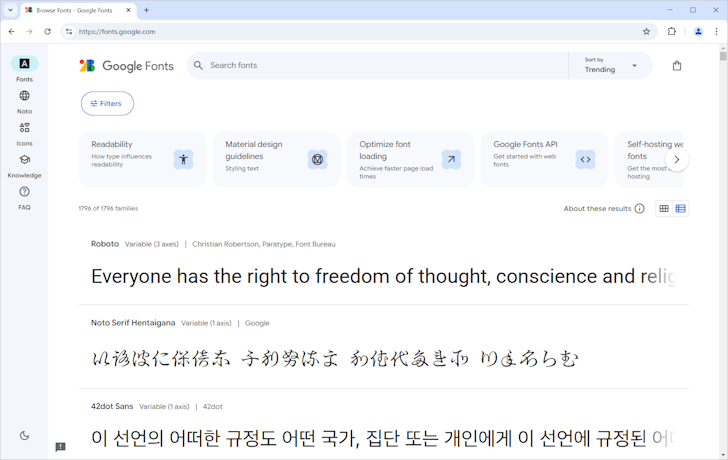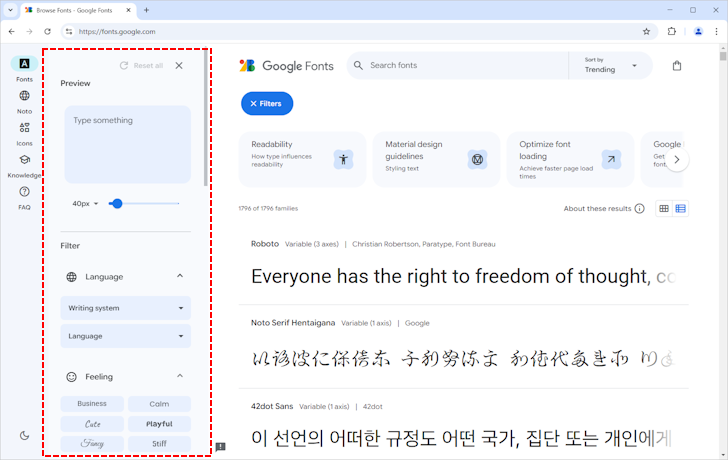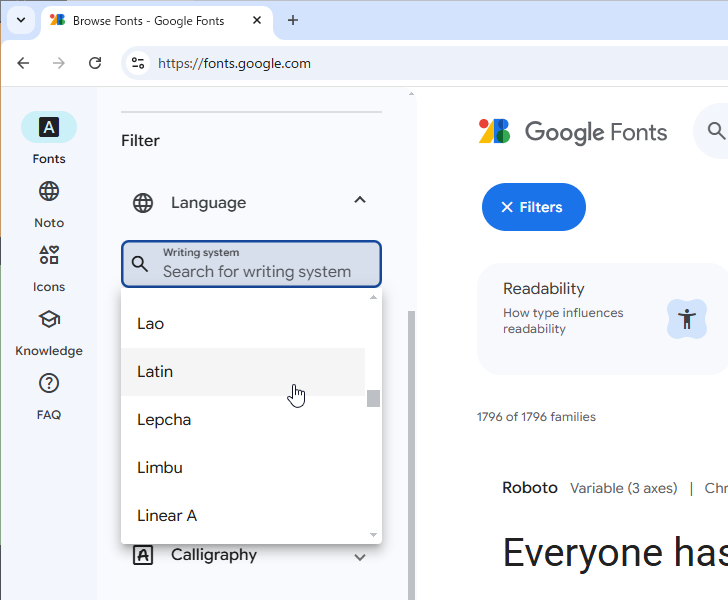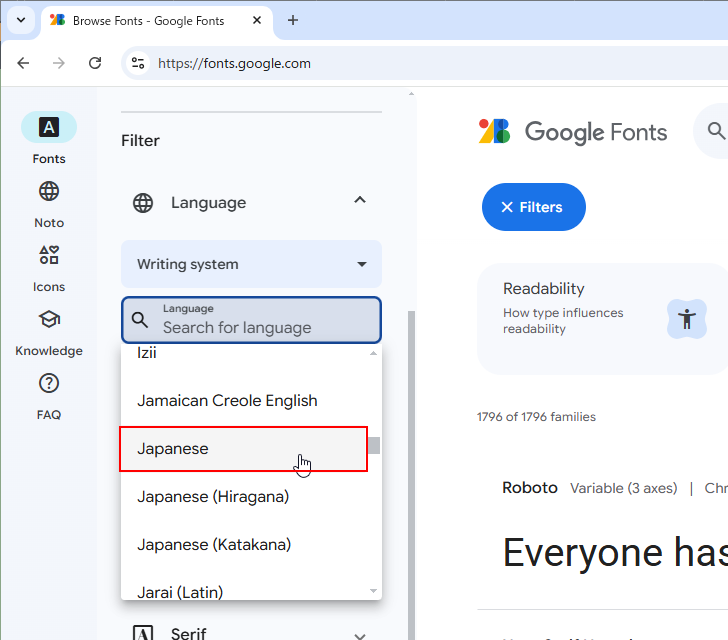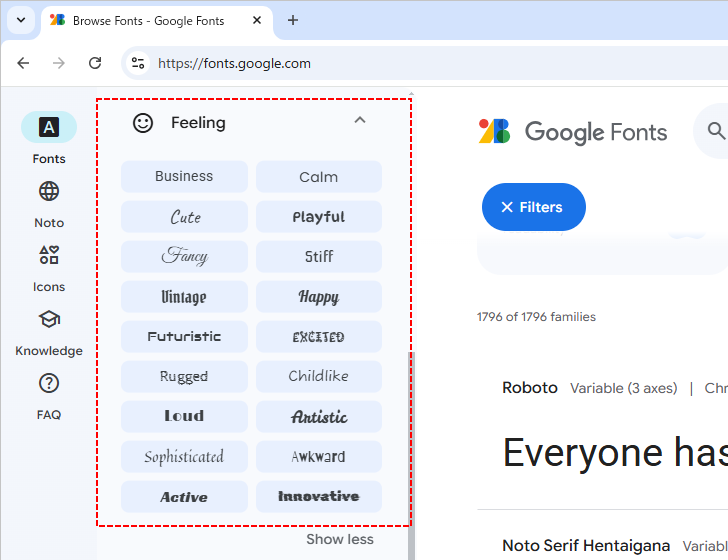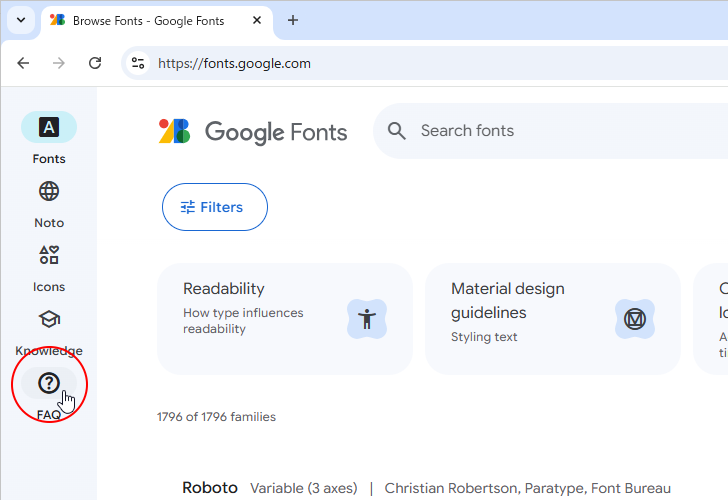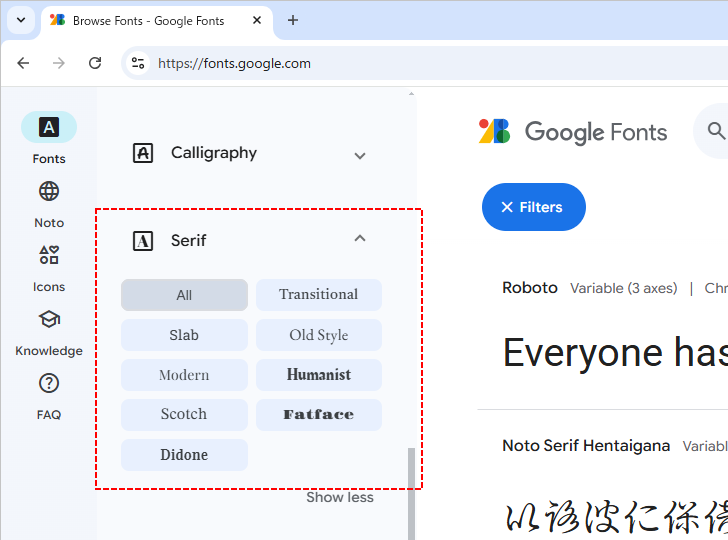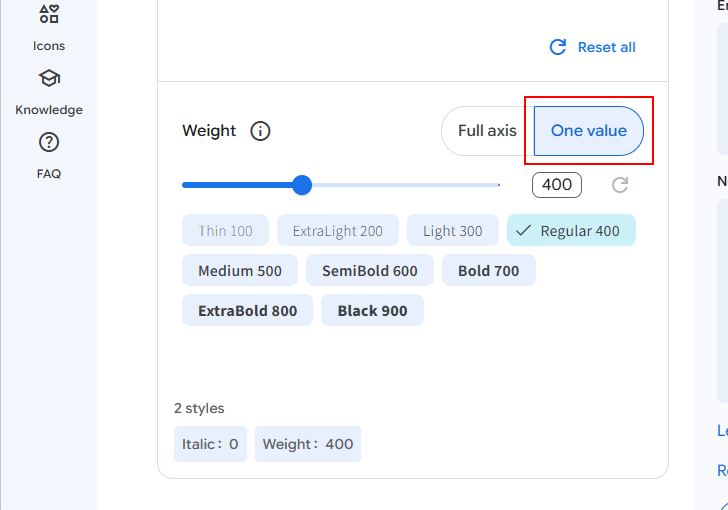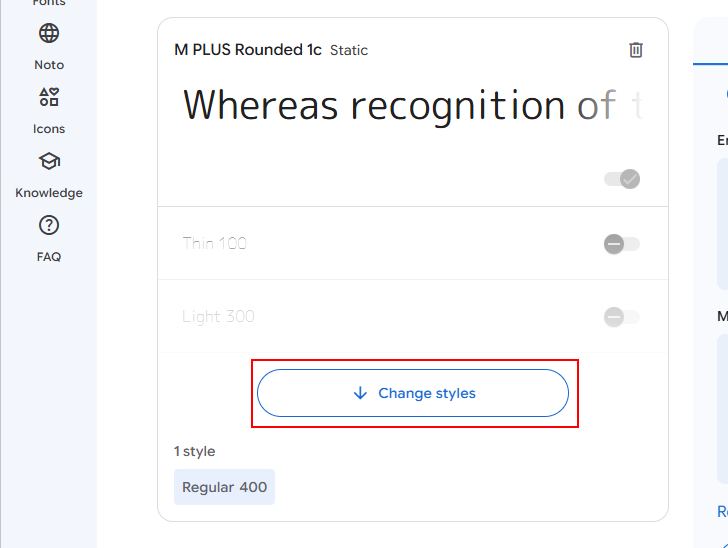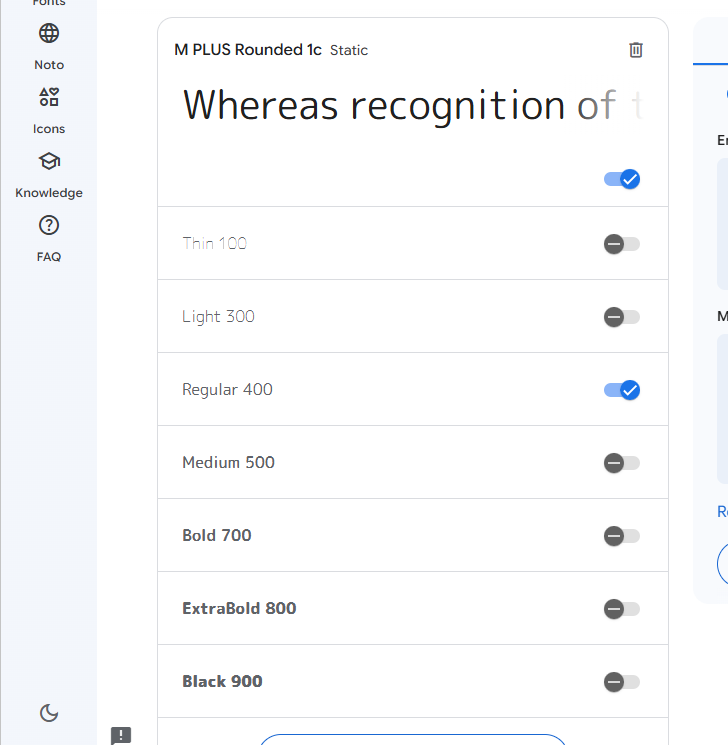
Google Fontsの使い方 ~初心者の方向けの完全ガイド~
Google Fonts は Google 社が提供している Web フォントサービスです。 Google Fonts はすべてオープンソースで、無料で利用することができます。商用目的での利用も可能で、 Web ページだけでなく印刷物やアプリ、教材、電子書籍などでも利用できます(詳しくはライセンスを確認されてください)。この記事では Web フォントとして Google Fonts を使う方法にについて詳しく解説します。
Google Fontsとは
目的のフォントを探す(フォント名を検索する)
利用するフォントを探す方法です。最初に使用したいフォント名が分かっている場合に、検索する方法です。画面上部の検索ボックスにフォント名(一部でも可能です)を入力して検索してみてください。
例えば Noto と検索すると、フォント名に Noto が含まれるフォントの一覧が表示されます。
このように利用したいフォントの名前が一部または完全に分かっている場合は、フォント名を検索するのが簡単です。
目的のフォントを探す(フィルターを使って条件に合うフォントを探す)
利用するフォントが決まっていない場合、フィルターを設定して色々なフォントの中から条件に一致するフォントを探すことができます。フィルターを設定するには、画面に表示されている「Filters」をクリックしてください。
画面左側にフィルターを設定するエリアが表示されます。
フィルターの種類として、 Language, Feeling, Appearance, Caligraphy, Serif, Sans Serif, Technology, Seasonal, Properties の 9 種類が用意されています。
それでは順番にフィルターの内容を見ていきます。
Language(言語)
Language は言語に関するフィルターです。日本語のフォントを探す場合など、利用される頻度が一番高いフィルターかと思います。 Language には Writing system と Language の 2 つのドロップダウンメニューがあります。
Writing system(書記体系)とは、特定の言語グループが使用する文字体系のことを指します。英語やドイツ語といった個別の言語ではなく、ラテン文字やアラビア文字のように、複数の言語で共通して使用される文字体系を指します。例えばラテン文字を使ったフォントを探す場合は Latin を選択してください。
Language はフォントの対象の言語を指定します。例えば日本語のフォントを探す場合は Language で Japanese を選択してください。
日本語のフォントの一覧が表示されます。
Feeling(感情)
Feeling はフォントが伝える雰囲気や感情を表すのに適したフォントを表示するフィルターです。
例えば Happy をクリックしてみると、 Happy な感情になれるフォントの一覧が表示されます。
Appearance(外観)
Appearance はフォントの視覚的な特徴やスタイルに基づいてフォントを表示するフィルターです。
例えば Techno をクリックしてみると、外観が Techno のフォントの一覧が表示されます。
Caligraphy(カリグラフィー)
Caligraphy はカリグラフィー風の装飾的なフォントを表示するためのフィルターです。
例えば Handwritten をクリックしてみると、手書き風のフォントの一覧が表示されます。
Serif(セリフ)
Serif は文字の端に小さな装飾(セリフ)が付いたフォントのことで、 Seif のフォントを表示するフィルターです。日本語では明朝体と呼ばれるものです。
例えば Modern をクリックしてみると、 Serif のフォントの中で Modern(現代的)なフォントの一覧が表示されます。
Sans Serif(サンセリフ)
Sans Serif は小さな装飾(セリフ)がないフォントのことで、 Sans Serif のフォントを表示するフィルターです。日本語ではゴシック体と呼ばれるものです。
例えば Rounded をクリックしてみると、 Sans Serif のフォントの中で Rounded(丸ゴシック)なフォントの一覧が表示されます。
Technology(テクノロジー)
Technology はフォントの技術のフィルターです。具体的に Variable をクリックした場合は可変フォント、 Color をクリックした場合はカラーフォント、 None をクリックした場合は Variable も Color も設定されていないフォントを表示します。(ただ可変フォントの中には Variable が設定されていないものもあり、 Variable をクリックしたときに、すべての可変フォントが表示されるわけではありません)。
例えば Color をクリックしてみると、カラフルなフォントの一覧が表示されます。
Seasonal(季節)
Seasonal は季節感や特定のイベントで使用するのに適したフォントを表示するフィルターです。例えば、クリスマスやハロウィンなど、季節や行事に適したフォントを探す際に使用します。
例えば Christmas をクリックしてみると、クリスマスに関するコンテンツを表示するときに適したフォントの一覧が表示されます。